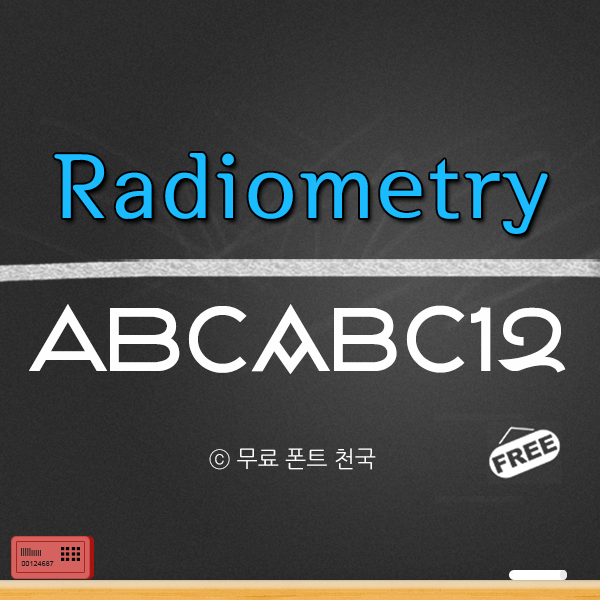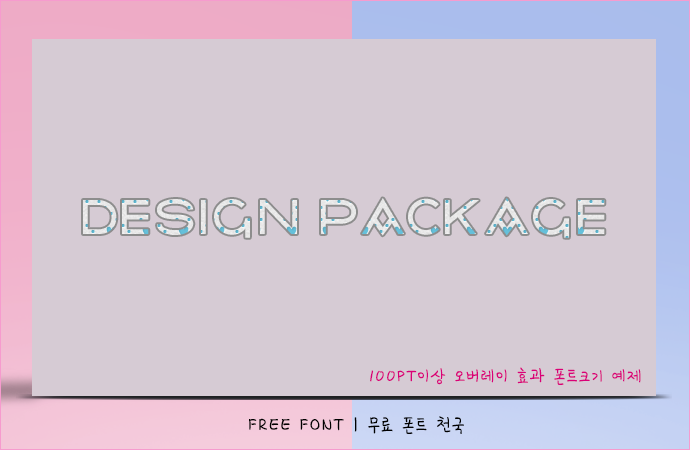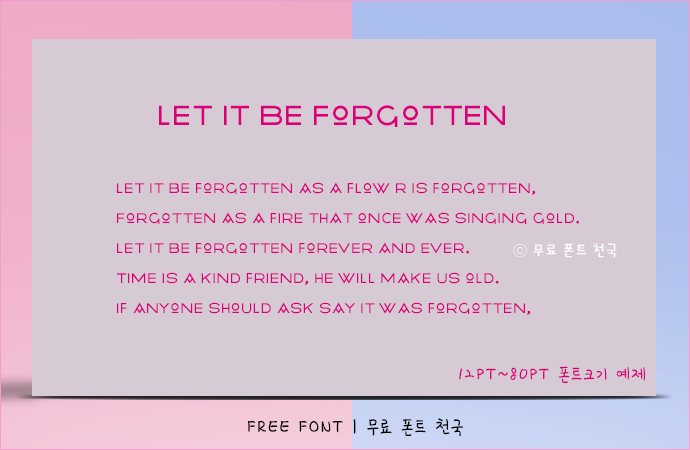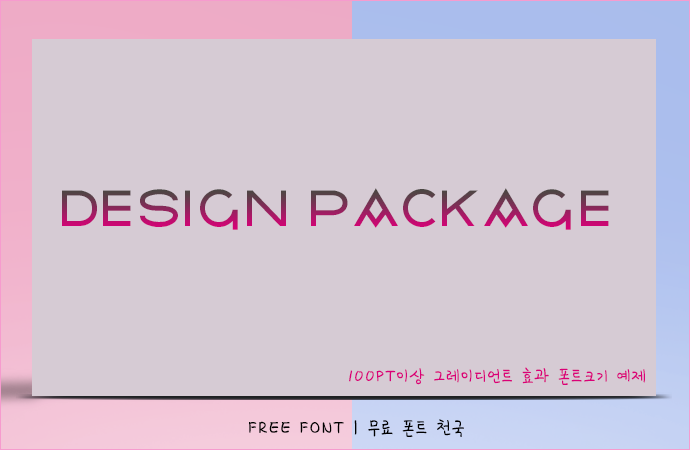
고대 문명의 서체 느낌 'Radiometry' 영문폰트
Radiometry 폰트 정보
특정 알파벳을 독특하게 제작해 고대 문명의 서체 느낌이 풍기는 Radiometry 영문 서체입니다.
글자체가 많은 본문에는 추천하지 않습니다.
Radiometry 폰트 # 미리보기
Radiometry 폰트, 12~80PT 크기로 적용한 효과
Radiometry 폰트, 100PT 크기 이상으로 작업한 오버레이 효과
Radiometry 폰트, 100PT 크기 이상으로 작업한 그레이언트 효과